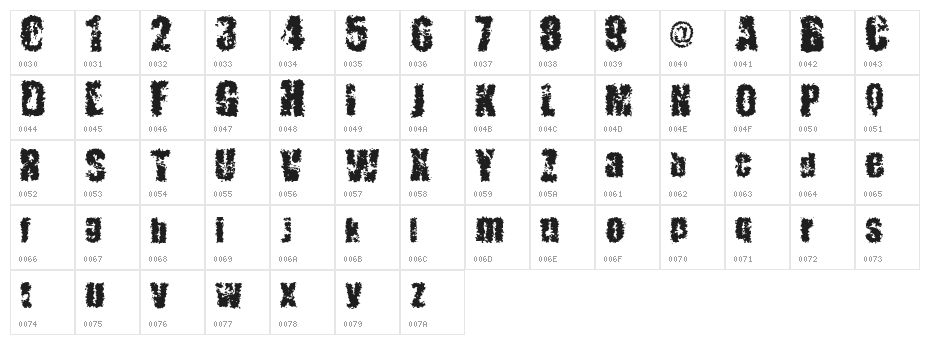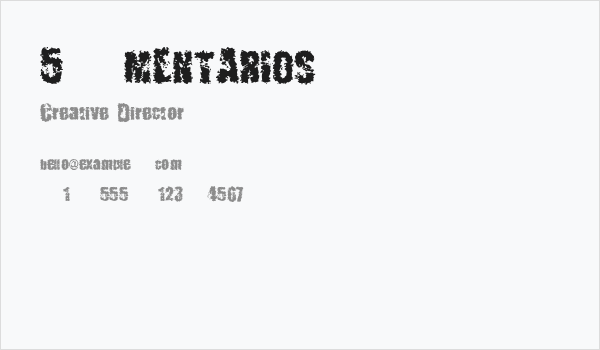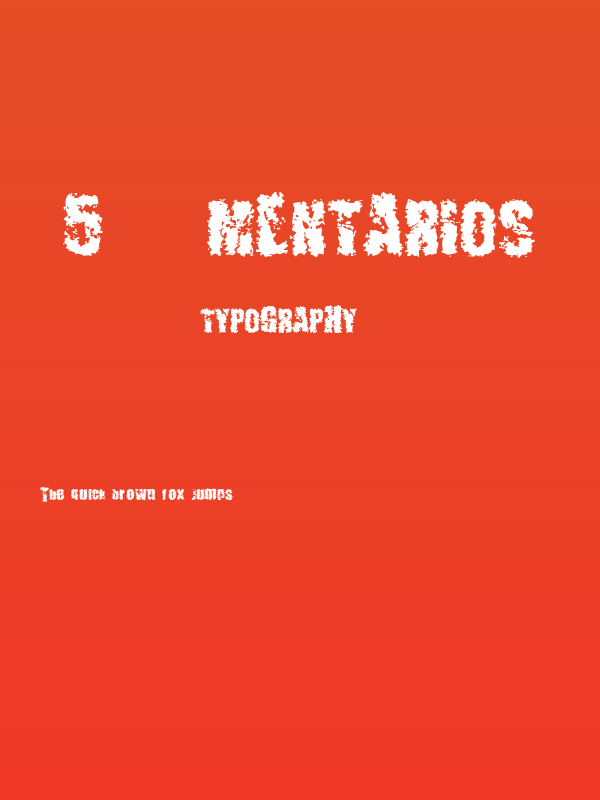
5+MENTARIOS Font
5-MENTARIOS 大文字
5-MENTARIOS 小文字
5-MENTARIOS その他の文字
| 名前 | 5+MENTARIOS |
| カテゴリ | Fancy |
| おすすめプロジェクト | Ideal for album covers, posters, branding for extreme sports, or any project needing a gritty, impactful look. |